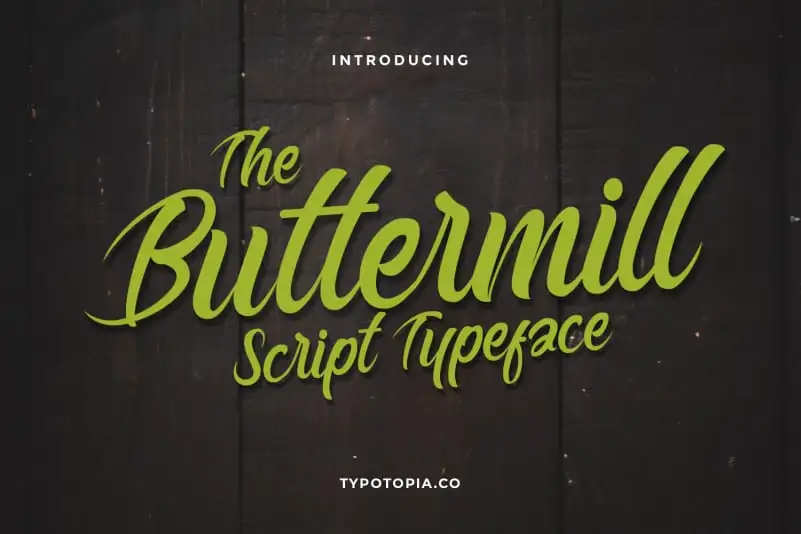
Buttermill Fancy Script Typeface – Download Grátis
A Buttermill Script Typeface é uma tipografia de script perfeitamente concebida para utilização em diversos ambientes, desde as identidades visuais de marcas até pequenos detalhes como embalagens e cartões de papelão. Sua elegância e fluididade a tornam um recurso valioso para designers buscando dar vida à sua arte digital ou impressa, especialmente quando se trata de elementos que precisam chamar a atenção. Seja para criar uma identidade visual única com um design de logomarca sofisticada, uma assinatura especial para um site ou produto, um card de visita criativo ou até mesmo a cara de uma capa de revista, essa fonte pode adicionar um toque singular e estilizado. A Buttermill Script é perfeita para personalizar itens como convites para festas, capas de livros com estilo, menus em lojas gourmet e etiquetas de embalagens criativas. Esta tipografia se destaca por sua facilidade de uso e versatilidade, o que a torna uma escolha inteligente tanto para designers gráficos profissionais quanto para quem busca adicionar um toque único a trabalhos pessoais. Seja qual for seu projeto – seja ele grande ou pequeno – a Buttermill Script pode ajudá-lo a destacar-se no meio da multidão e capturar o olhar do público com uma expressividade única.